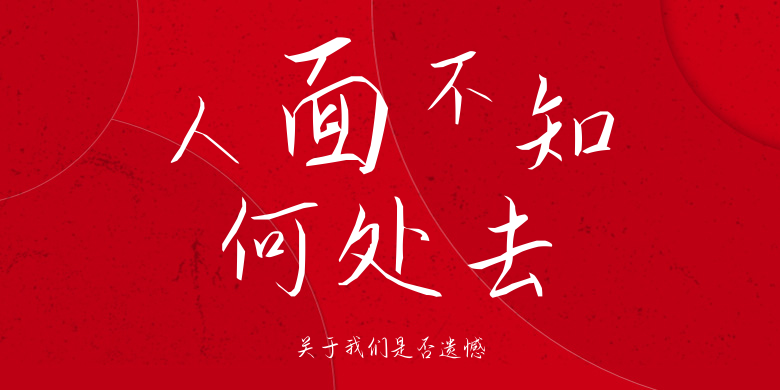
关于我们是否遗憾
关于我们是否遗憾,这款字体结构工整、笔画清晰,兼顾美观与易读性,适用于标题、正文、海报、包装、LOGO 等多种场景。字形优雅稳定,风格百搭耐看,适配日常排版与创意设计,让文字呈现更舒适、更具质感。关于我们是否遗憾一笔一画,皆是细节,以均衡的比例、流畅的线条打造舒适视觉体验,字形端正大气,风格简约现代。无论是商业设计、品牌宣传还是日常排版,都能轻松驾驭,让文字更有格调与力量。关于我们是否遗憾字体下载。